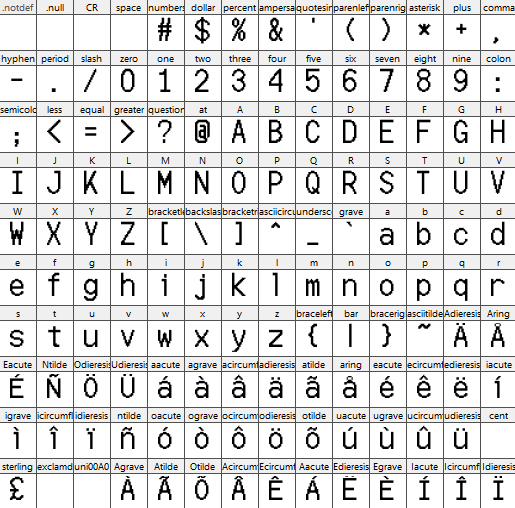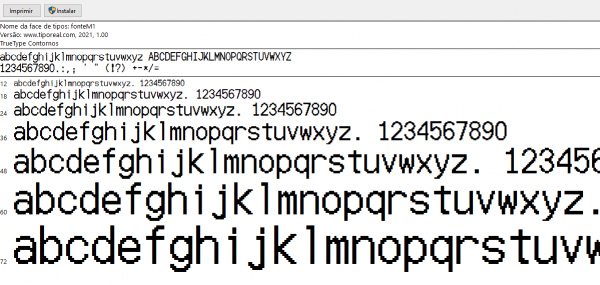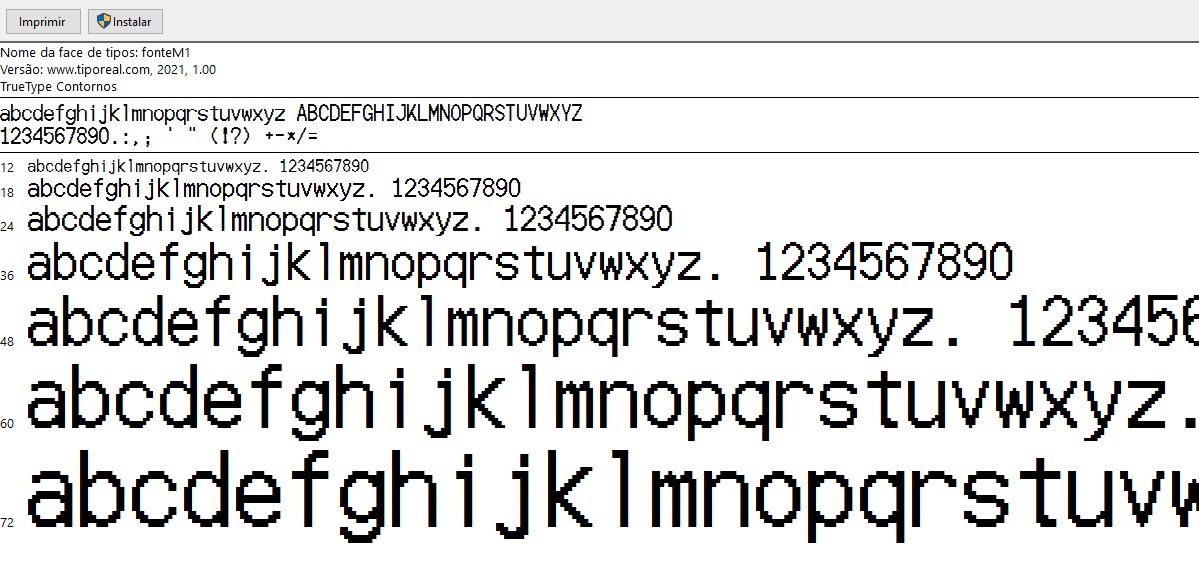
fonteM1
Amostra impressa da fonteM1 para fatura simplificada de McDonald’s em Portugal (❶fonteM1-negrito ❷fonteM1)⤴
Amostra impressa da fonteM1 para fatura simplificada de McDonald’s em Portugal⤴
Todos os personagens⤴
O que parece quando aberto com o visualizador de fontes padrão do Windows⤴